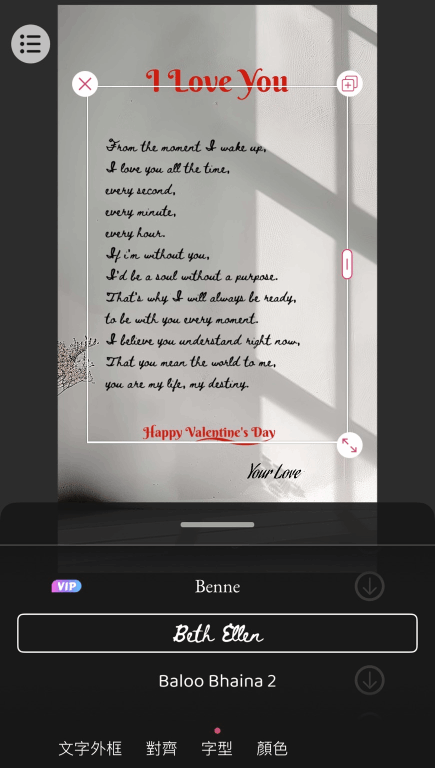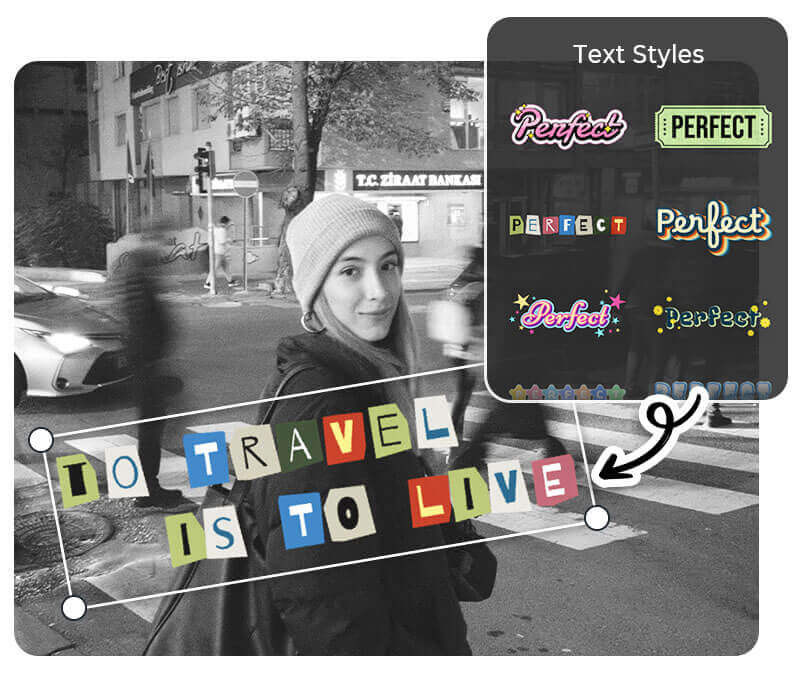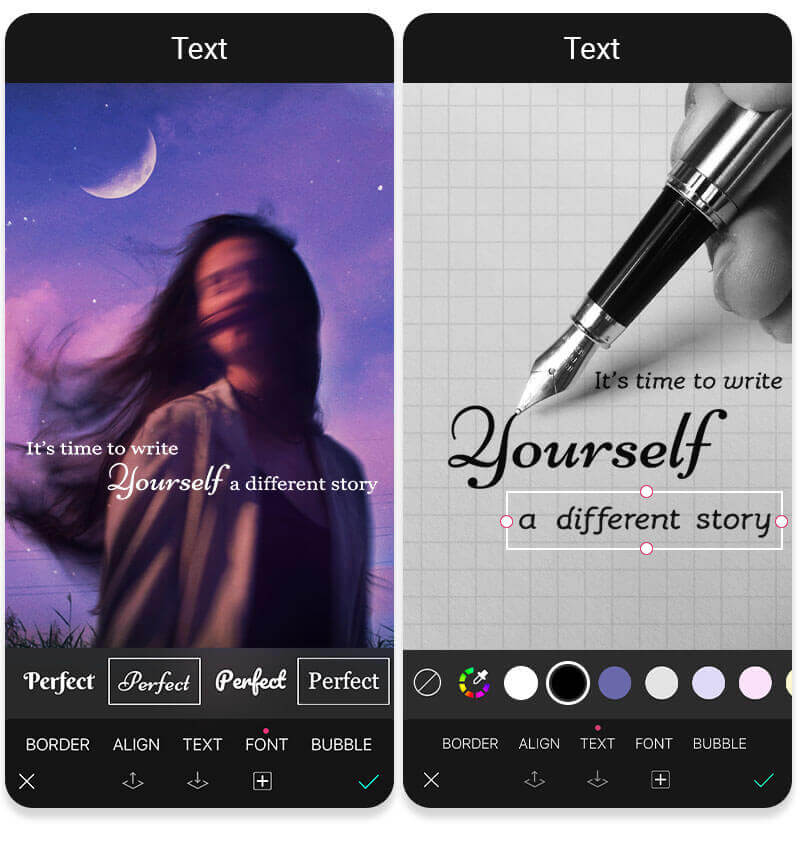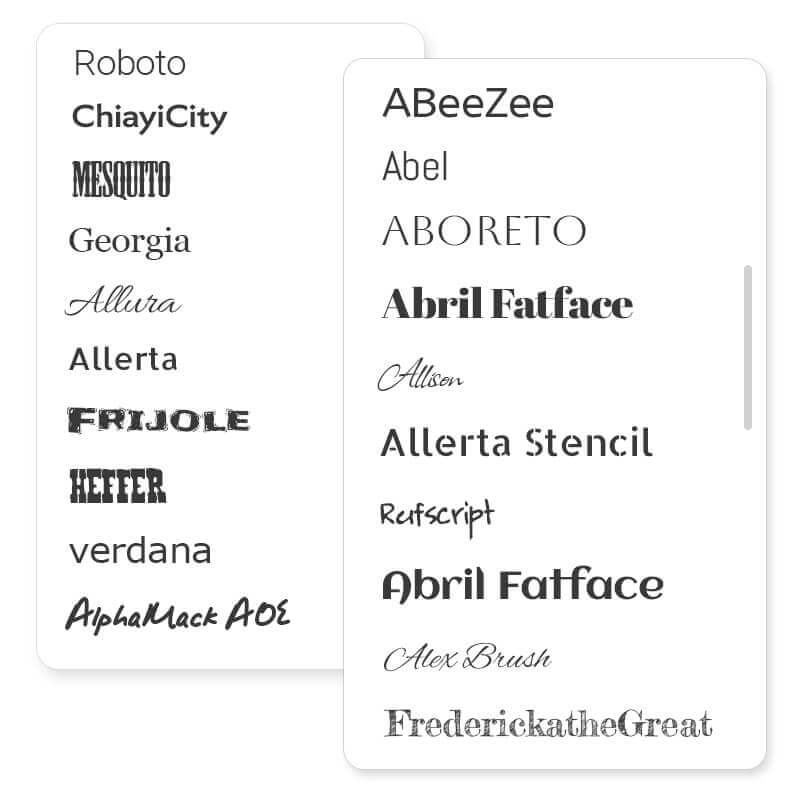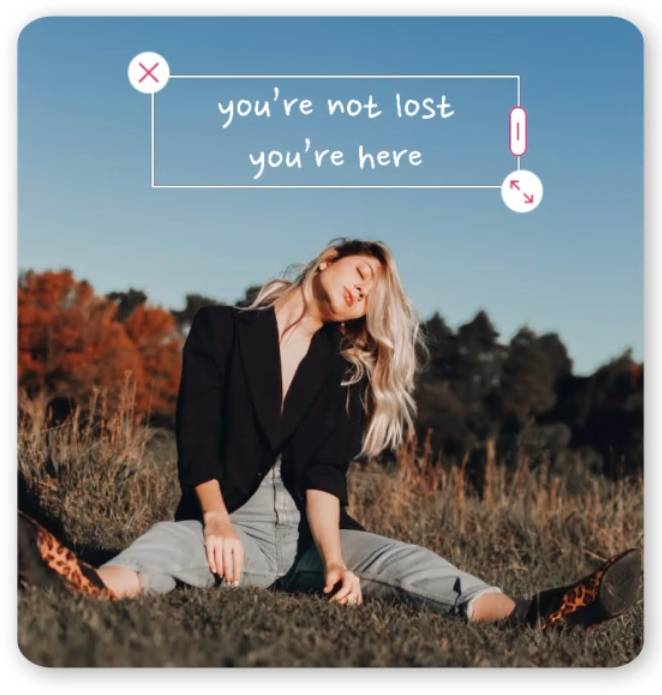
特殊英文字體產生器!300+ 草寫、可愛、質感英文字體轉換
特殊英文字體產生器!草寫、可愛、質感英文字體轉換
當你剛拍了一張完美展現當下氛圍的自拍照,或想發一張照片在 IG 限動,想要為照片添加一些文字說明。
透過英文字體產生器,不僅能輕鬆讓你挑選喜歡的字體風格,還能幫助你打造專屬的照片效果,讓你的照片更具創意和美感:
▲ 透過【玩美相機】英文字體轉換器,將文字轉換成草寫、可愛、質感英文字體
以下我們將介紹一款有 300+ 英文字體的字體轉換器,,讓你能夠和以往不同的方式來編輯照片。
特殊英文字體產生器推薦!300+ 英文字體轉換
玩美相機是一款內建300 + 特殊英文字體的字體產生器,讓編輯文字變得簡單又快速,並提供多種文字顏色選擇以及大量的字體,並同時擁有多樣的照片編輯工具:
特殊英文字體產生器
▲ 使用這款英文字體產生器編輯過程非常簡單,只需點擊文字功能即可開始產生文字
300+ 英文字體選擇
300+ 英文字體
這款字體產生器提供超過 300 種字體可供選擇,你可以根據照片的氛圍,打造最符合心情的文字效果。
從經典風格字體到藝術風格和手寫字體,你理想的字體就在這裡等著你!
特殊風格英文字轉換
另外你還可以使用【文字風格】功能生成具有裝飾的英文字體,讓你的 IG 限動、宣傳圖文輕鬆變好看*此功能目前僅支援 iOS
如何使用英文字體轉換器轉換質感英文字體
• 步驟 3:滑動底部工具列,點擊文字選項
• 步驟 4:輸入英文文字,選擇你喜歡的質感英文字型
• 步驟 5:調整文字外框、顏色、粗體、斜體等
• 步驟 6:或套用文字風格功能,讓文字變成藝術英文字體
手寫、草寫、質感英文字體推薦
如果你已準備好使用英文字體轉換器,不妨在測試添加英文文字到照片時,試試以下字體:
• 手寫風格英文字體
• 質感英文字體
• 草寫英文字體
手寫風格英文字體
手寫風格英文字體▲ 嘗試可愛手寫風格或鋼筆風格的英文字體
質感英文字體
▲ 質感手寫或可愛印刷英文字體
草寫英文字體
▲ 結合照片編輯功能與文字功能,用草寫英文字體製作質感圖片
結語
現在透過英文字體產生器玩美相機,讓你的照片加上漂亮的手寫、草寫、可愛、質感英文字體吧!